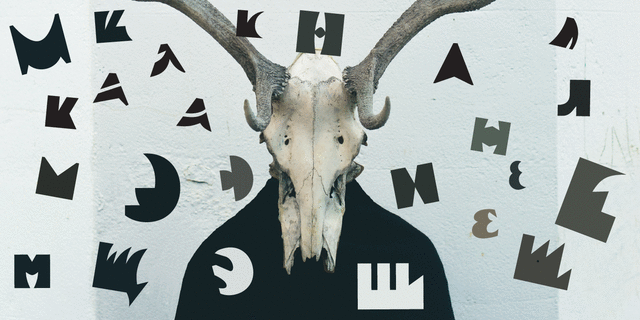
Ардент – это шрифт, вдохновленный поздними работами гениального русского художника Сергея Чехонина. Ардент доказывает, что причудливые, революционные кириллические формы букв 20-х годов до сих пор применимы в современном дизайне, даже в латинице. Рисунок шрифта крайне прост и, в то же время, орнаментален, поэтому его нужно использовать очень аккуратно и осознанно. Ардент поддерживает множество языков. Этот шрифт заставляет вас воспринимать букву не как набор штрихов (жирных или тонких) а как пятно. Черные массы с разнообразным силуэтом активно взаимодействуют с белым пространством. Ардент поддерживает все возможности OpenType. Например вы можете использовать случайный выбор глифов для определенных букв, благодаря контекстным альтернативам. Ардент – это живой организм, буквы сами меняются во время набора. Цифры также работают лучше всего, если включить контекстные альтернативы. Также Ардент прекрасно подходит для буквиц в сочетании с нейтральными текстовыми шрифтами и для трафаретов. Шрифт разработан Дмитрием Голубом и выпущен в студии Thundertype в 2015 году.